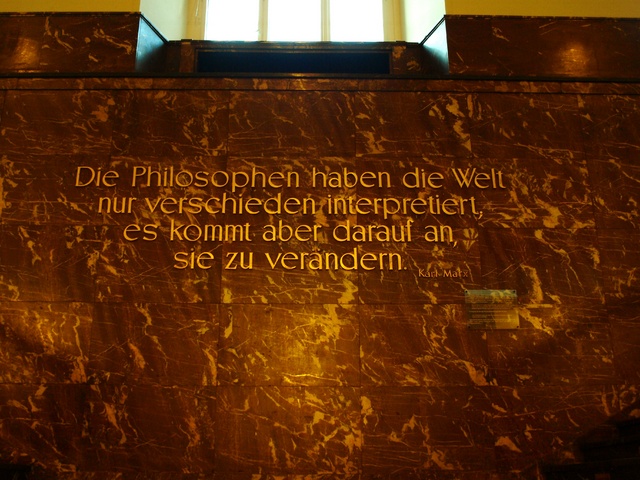
Welche Schrift wurde hier verwendet?
ich bin ein völliger typographischer Laie und versuche hier Hilfe zu bekommen für eine Arbeit zu DDR-Typographie. Und zwar würde ich sehr gerne wissen welche Schrift für das Marx-Zitat im Hauptgebäude der Humboldt-Uni verwendet wurde. Keine Ahnung ob das hier jemand anhand von Fotos beurteilen kann.
Um diese Schrift geht es:
Da hat doch irgendwer sein eigenes Ding gemacht, oder?!
Hat so ein bisschen was von der Caslon (mit abgeschnippelten Serifen) und der Stahl.
So ganz stimmig ist das aber alles nicht, wenn man alleine mal das n und e vergleicht ...
Ich glaub nicht, daß das eine Satzschrift ist. Vermutlich hat man einen Kalligrafen beauftragt und und dessen Vorlage verwendet.
Die Schrift kommt mir vor wie ein Mix aus Optima (und verwandten serifenlosen - was die Buchstabenform und Dickten angeht) und Ed Benguiat Schriften (Panache oder Avantgarde - was die etwas "jugendstilige" Rhythmik der Buchstaben z.B. mit den schmalen n angeht). Wenn das wirklich in den 50ern entstanden sein sollte, war das damals extrem modern und seiner Zeit fast voraus ...
Mit einer (damals) typischen DDR-Schrift hat das alles wenig zu tun. Da hatte jemand entweder Westverwandschaft oder zumindest einen sehr guten Blick aufs internationale Schriftschaffen ...